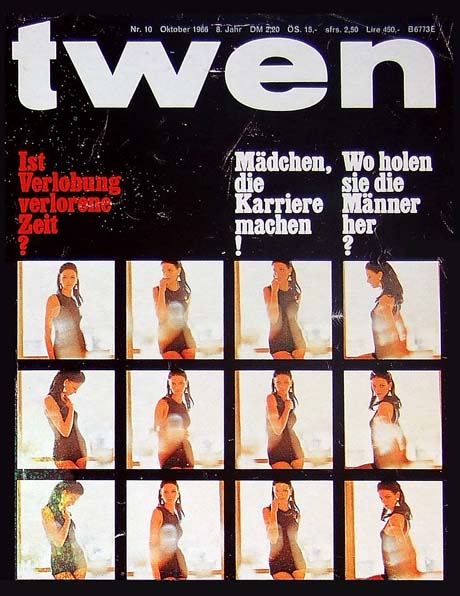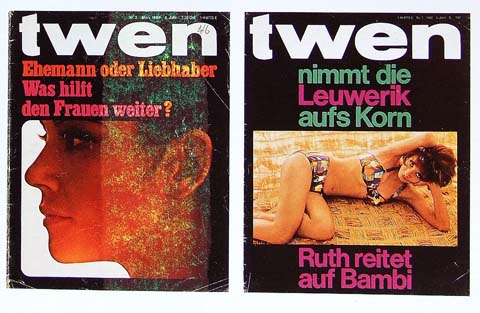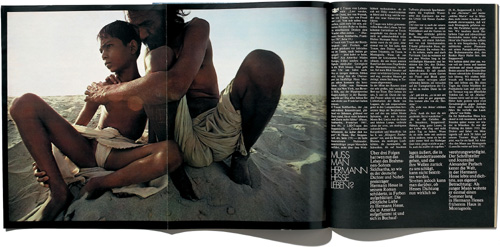
Twen MagazinA revista alemã dos «soft sixties», foi concebida por Willy Fleckhaus. A revista, que se publicou de 1959 até 1971, marcou novos padrões estéticos. A Twen foi um fenómeno especificamente alemão, mas a sua qualidade fê-la atravessar as fronteiras geográficas.Foi concebida como revista para jovens adultos. Desde o início se definiu pelo excelente layout de Willy Fleckhaus, assim como pelas fotos de reportagem e de moda (com destaque para Will McBride), e bons ilustradores como Hans Hillmann ou Heinz Edelman. O ritmo com que as fotografias são dispostas nos spreads e a noção de contraste de densidade e escala são as marcas de Fleckhaus, que desenhou inúmeros livros para a Suhrkamp mas que teve aqui, nos anos certos e com os temas certos, a sua consagração. Twen Revision Einer Legende (Revisão de uma Lenda) de Michael Koetzle. 330 p., Munchner Stadtmuseum, 1995.
Twen Magazin viu a luz do dia na Primavera de 1959. A revista vanguradista da Alemanha do pós-guerra combinava a força da tipografia da Bauhaus com o encanto do graphic design norte-americano. Pelas páginas da Twen desfilaram personagens do mundo da música, da moda, do cinema. Temas considerados tabus nesta época foram postos em foco - como o aborto e a homosexualidade. Contudo nunca atingiu o impacto das publicações muito mais extremistas, revolucionárias e críticas da época de 68.